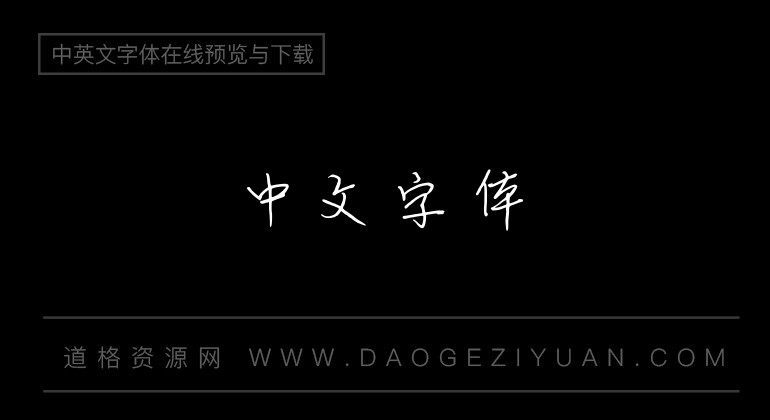
邢世新硬笔行书简体
邢世新硬笔行书简体字体是一款硬笔行书字体,由邢世新设计,源自中国硬笔书法古典文化,体现出传统书法的精髓,并结合现代技术技术,增加了更多的细节,从而使字体更加精致、灵动、细腻。此外,邢世新硬笔行书简体字体还具有良好的可读性和可辨识度,可以满足不同类型的文本需求。
邢世新硬笔行书简体是一款非常不错的手写艺术字体,具有很好的视觉感,适合于文化类的宣传设计、商业类品牌的广告和产品包装设计以及个性化文字排版等较多场景。